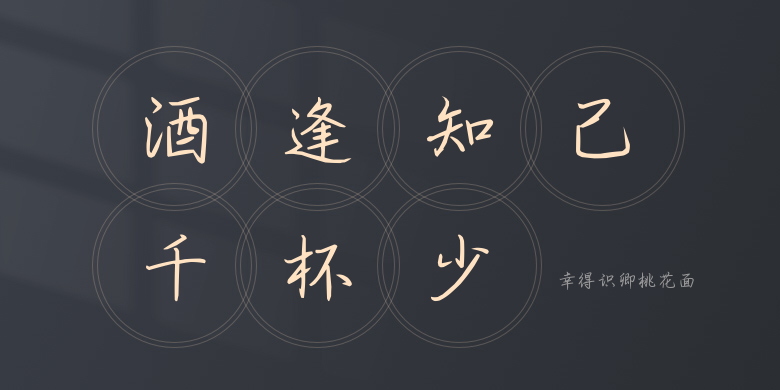
幸得识卿桃花面
幸得识卿桃花面,这款字体结构工整、笔画清晰,兼顾美观与易读性,适用于标题、正文、海报、包装、LOGO 等多种场景。字形优雅稳定,风格百搭耐看,适配日常排版与创意设计,让文字呈现更舒适、更具质感。幸得识卿桃花面一笔一画,皆是细节,以均衡的比例、流畅的线条打造舒适视觉体验,字形端正大气,风格简约现代。无论是商业设计、品牌宣传还是日常排版,都能轻松驾驭,让文字更有格调与力量。幸得识卿桃花面字体下载。